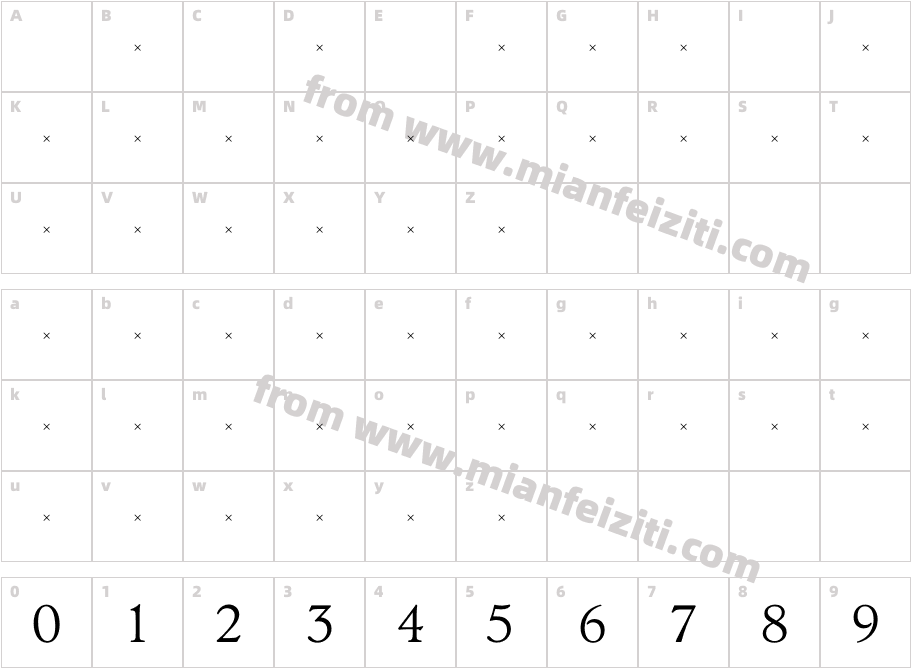
Stanhope Light Tab
字体名称: Stanhope Light Tab
Postscript名称: StanhopeLightTab
字体版本: Tab Version May 1993
Stanhope Light Tab预览图1
Stanhope Light Tab预览图2
Stanhope Light Tab字体映射图